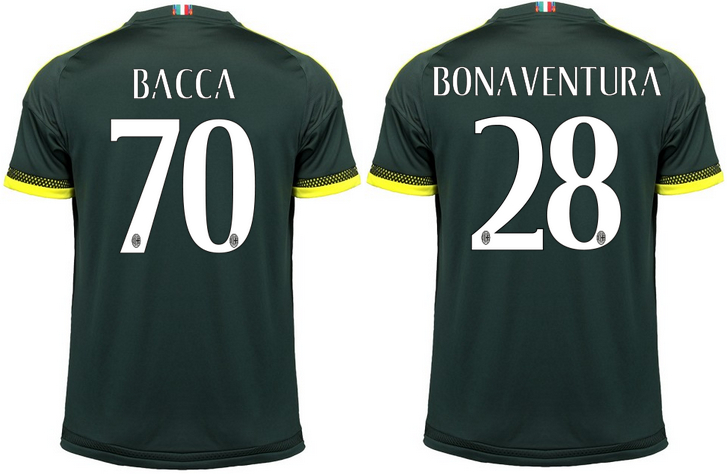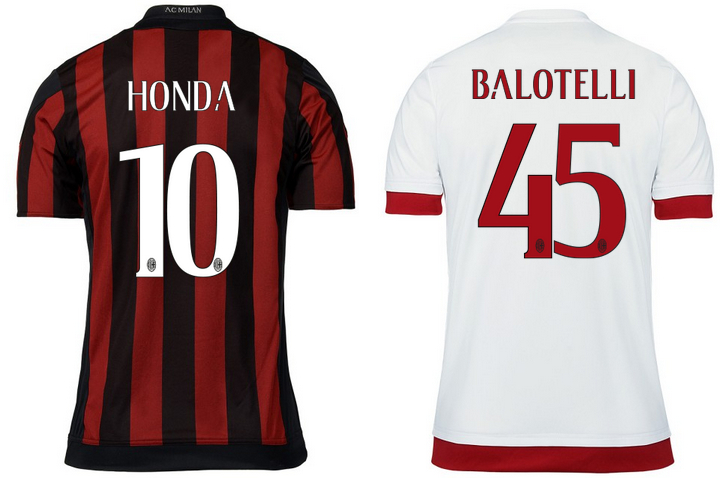
一方、ミランの今季ユニフォームは黒5本赤4本の伝統的なストライプ柄を採用。
フォントはこんな感じ。こちらは新しいものではなく昨季からの継続のはず。
個性的なインテルと比べると、どちらかと言うとオーソドックス。
そのなかで、ネームのAの綴りは特徴的。そして、クラブロゴが数字の中央部ではなく、すこしずれた場所に配置されているのも、インテルと違うところだ。
“背中”を見ても対照的な両チーム。今夜の決戦の行方は果たして…。